#源ノ明朝 のリリースと #フォントの日
4月10日に開催された「源ノ明朝」新しいPan-CJKフォントの誕生および「フォントの日」制定記念イベントに参加しました。
レポートを兼ねて、フォントの日、源ノ明朝についてまとめてみます。
っていうか、これ、手書きだったんだ!
源ノ明朝
源ノ明朝が4月3日にリリースされました。
源ノ角ゴシックと同様、3つの名前を持ちます。ウエイトも、同様に7ウエイト用意されています。
- 源ノ明朝
- Source Han Serif
- Noto Serif CJK
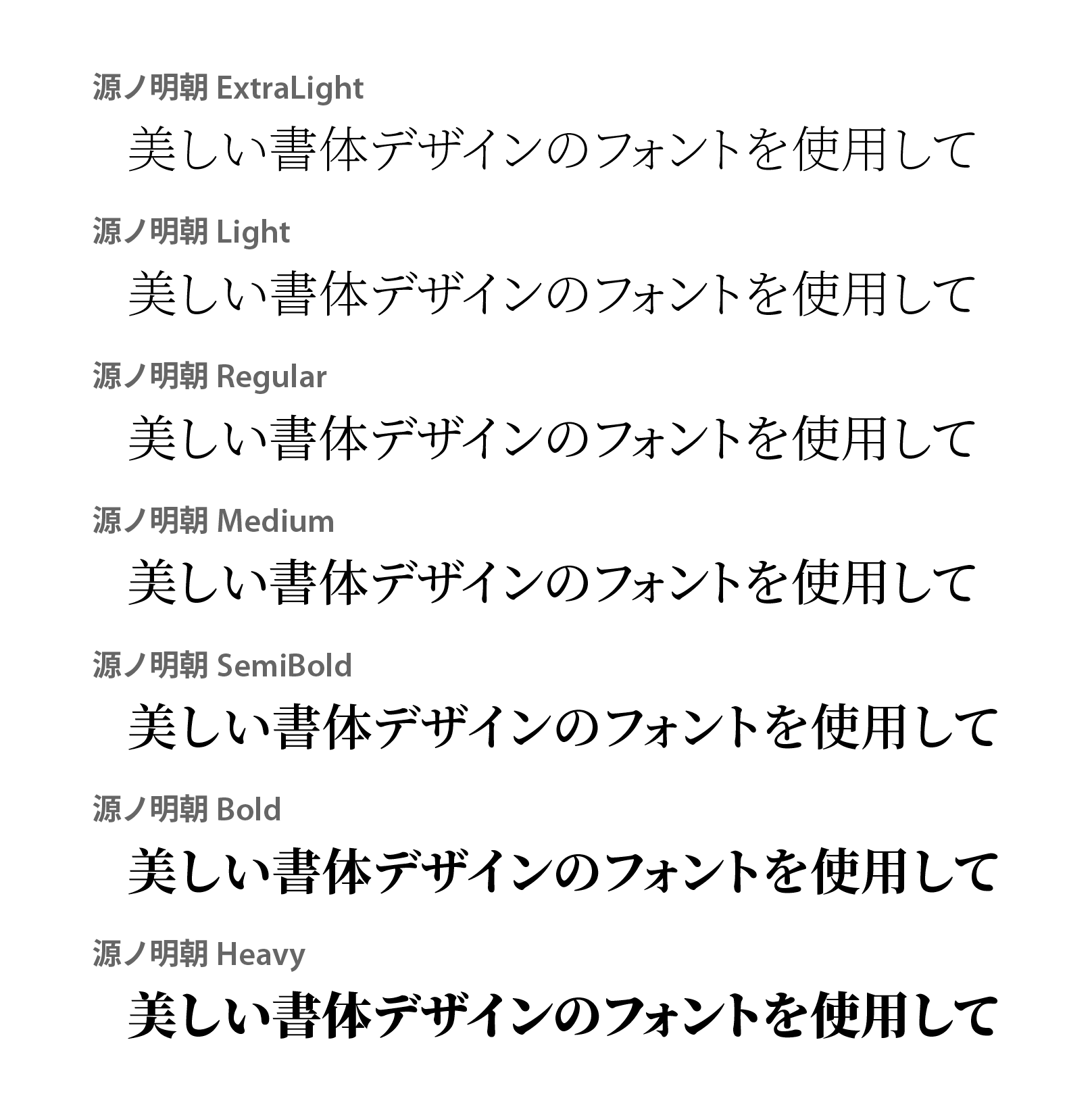
デザイン
「大きめの字面に対して、クラシックなフォルム」と解説されていました。
スモールデバイスでの表示を意識していることもあり、こうして比べてみると、横棒が圧倒的に太いですね。
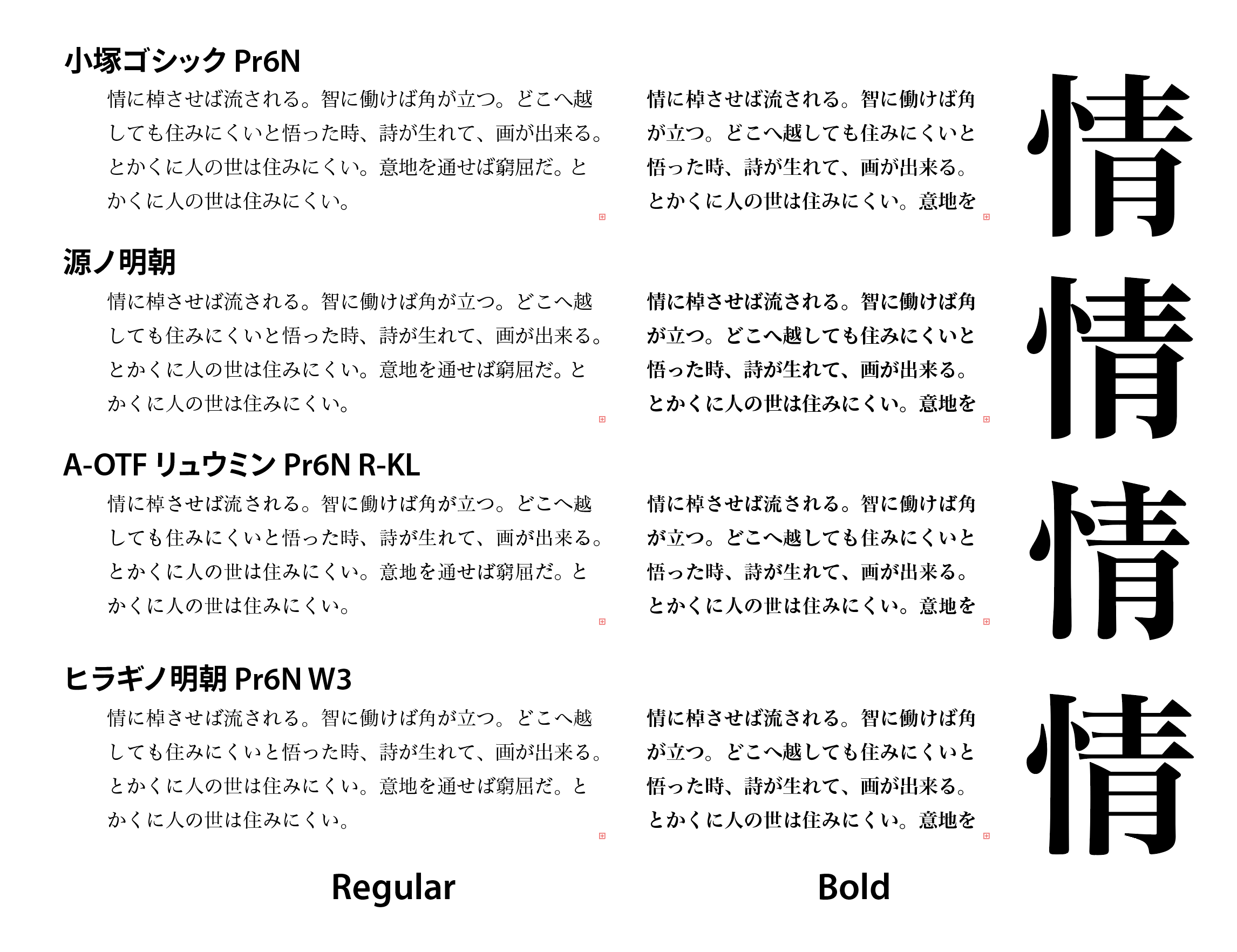
「源ノ明朝」というネーミング
- 「Source」をキーワードに名称を検討
- ソースだと「焼きそば明朝」と呼ばれてしまうかもと日本サイドで反対(こっちのソースはsauceだけど)
- Sourceを意味する「源」を使用することに
- フォント名としての固有性を高めるために「の」を追加。『風“の”谷のナウシカ』や『魔女“の”宅急便』のようにジブリメソッドを踏襲
ポイントはPan-CJK
CJKは、Chinese、Japanese、Koreanの略。東アジアで用いられている4つの言語(日本語、簡体中国語、繁体中国語および韓国語)で必要な文字をサポートすることが開発コンセプト。「Pan-」は、「全〜」といった意味合い。
ホテルや美術館など、多言語で掲示する必要があるケースでも、これまでは、フォントがないばかりに、不自然なフォントが使われていたり、
スーパーOTC
源ノ明朝および源ノ角ゴシックは、スーパーOTCに対応しています。
言語ごとにバラバラに使うだけでなく、それらを統合した1フォントとして使うことができるというもの。
Illustrator、InDesignでの利用
ウエイトの順番
Illustratorも30歳とのことで、そろそろ「アルファベット順」じゃなくて「ウエイト順」に表示してくれてもいいのにな、と思いません?
でも、冷静に見たら、「アルファベット順」でもなかった。何順??
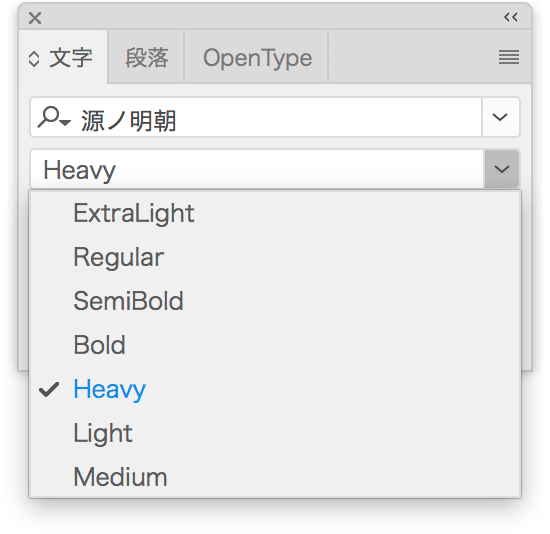
InDesignは、ウエイト順です…
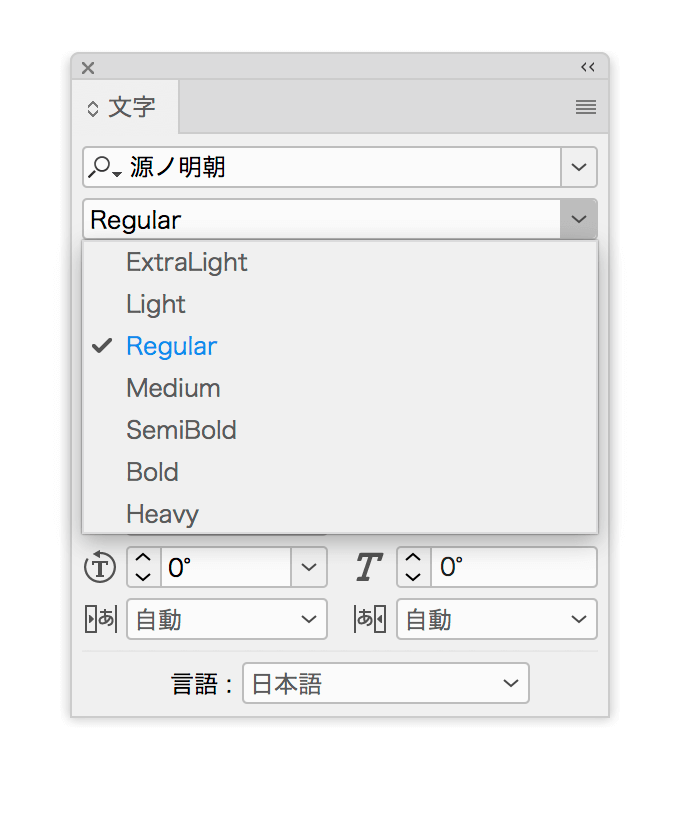
濁点
「源ノ明朝をこんな風に使って欲しい」というサンプルとして、次のスライドが提示されました。
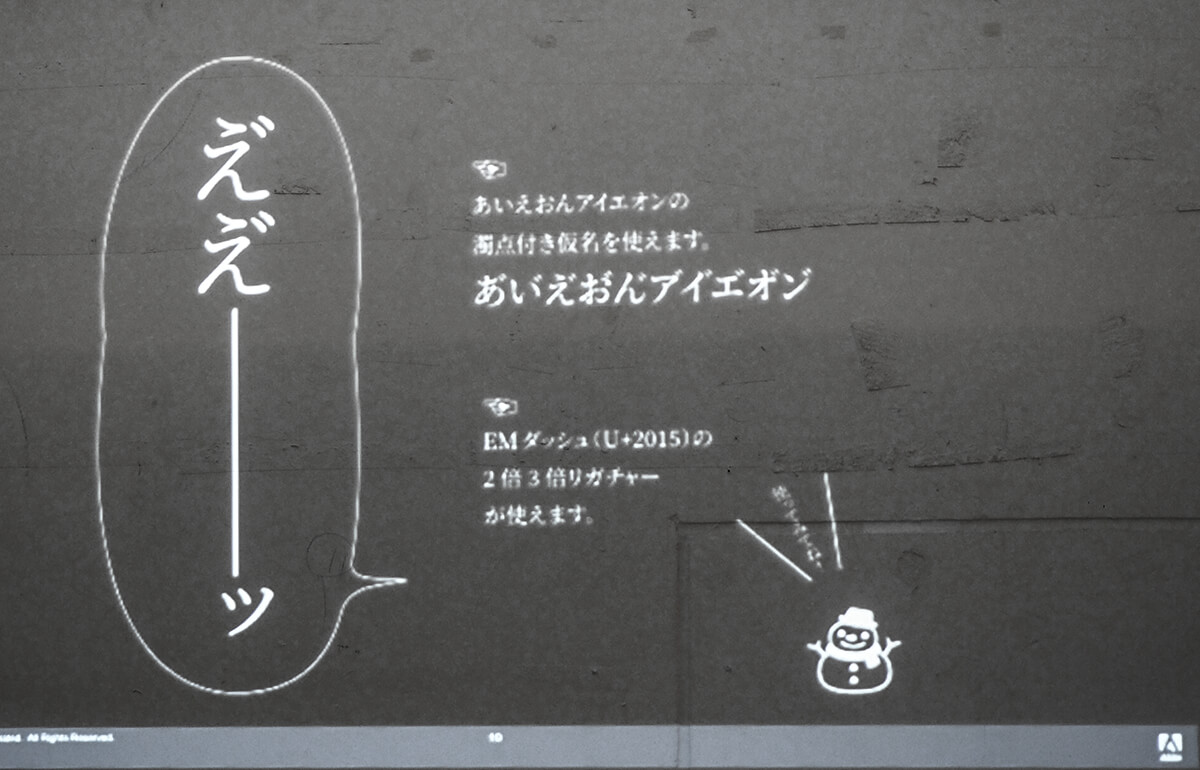
「え」に続けて、「゛」(だくてん)を入力すると、「濁点のついた“え”」になるハズですが、私の環境では、なぜかなりません。
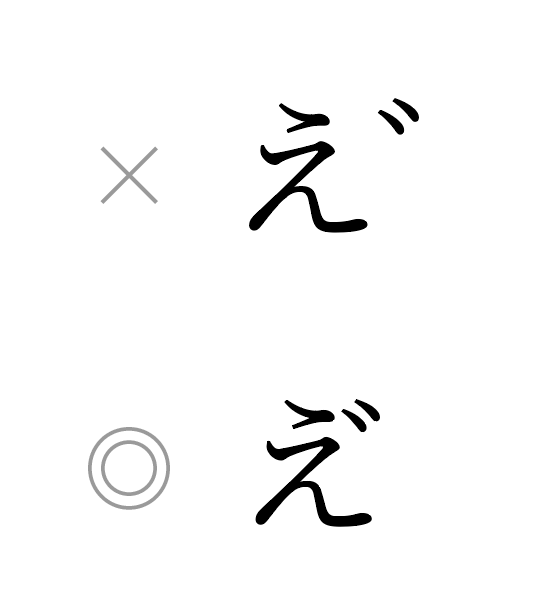
[字形]パネルの一番下の方にスクロールして、直接入力することはできます。
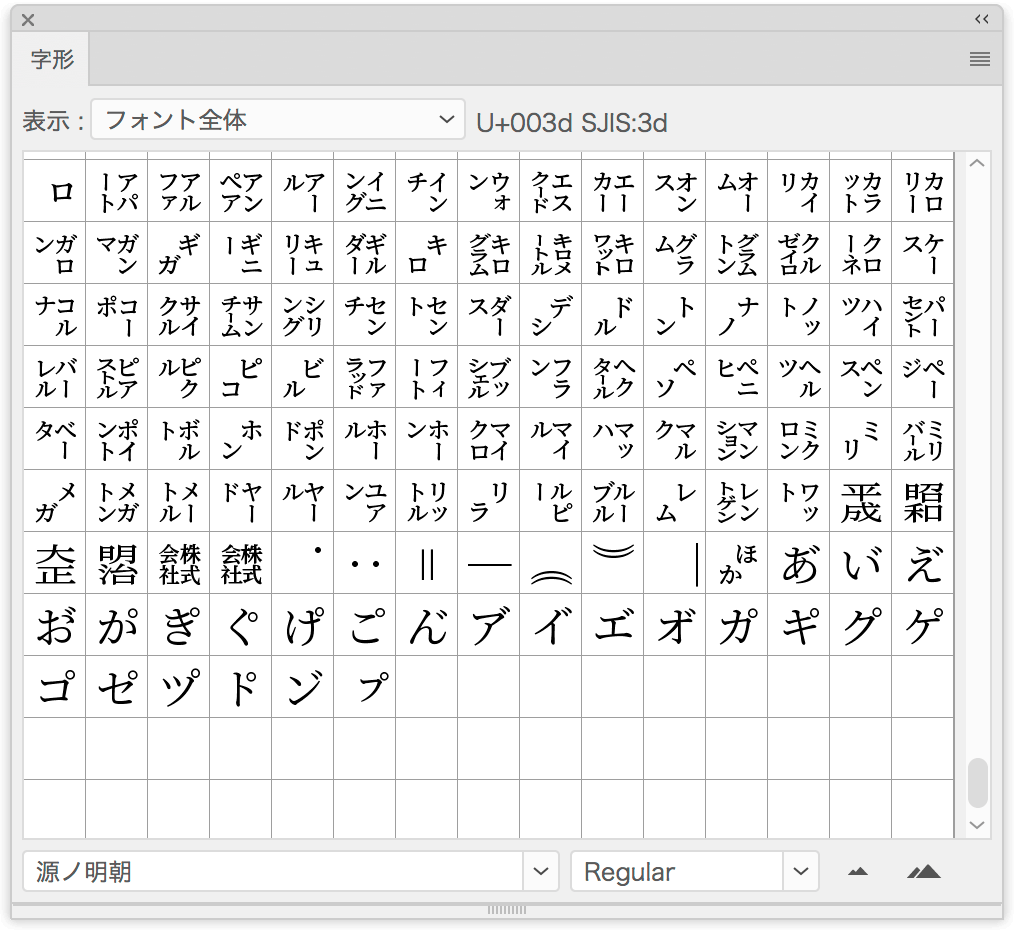
InDesignで調べてみると、確かに「309B」。
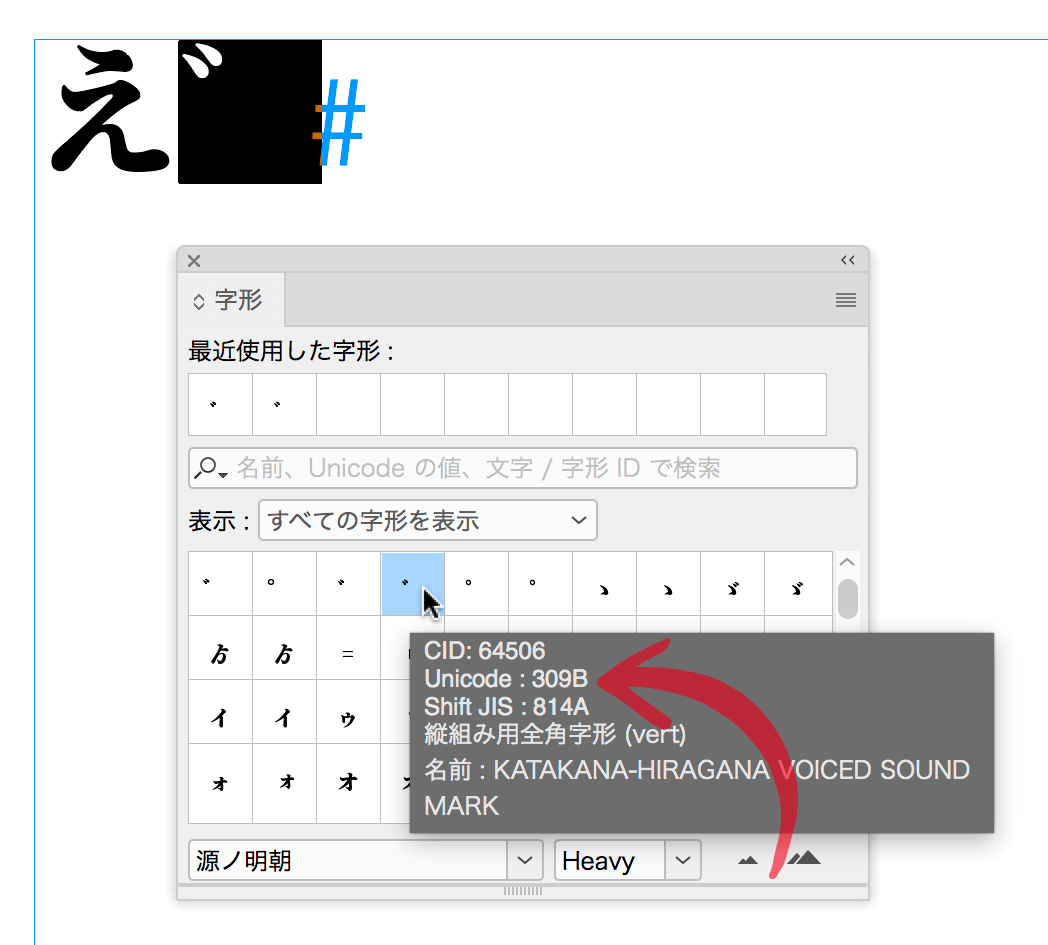
[字形]パネルの検索フィールドで「3099」を入れると、ちゃんと「濁点付きのえ」に変換されました。
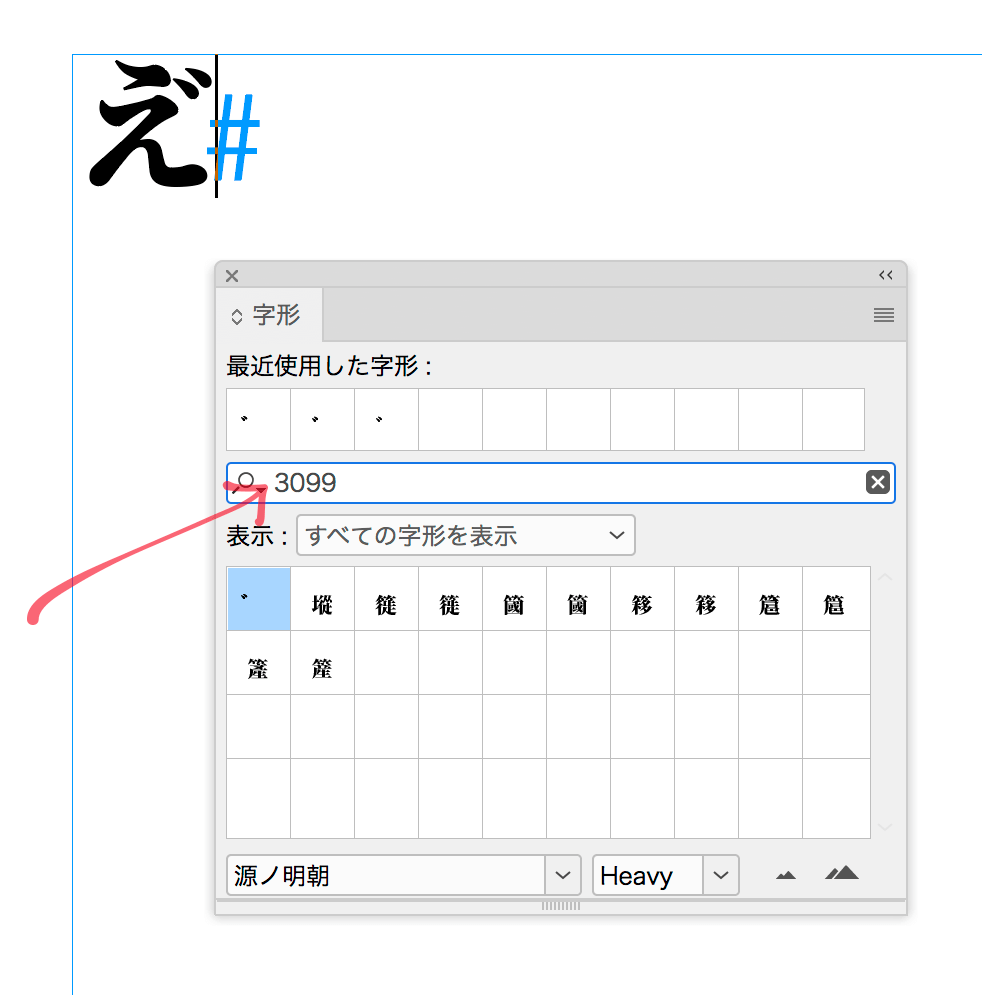
「3099」の濁点を単語登録したところ、IllustratorでもOKでした。
二倍ダーシ/三倍ダーシ
源ノ明朝では、ダーシを2つ、または、3つ続けて入力すると、合体したものに変換されます。しかし、Illustratorでは、縦書きのときに中心がズレてしまいます。
縦書きのときには、グリフを変更します。
縦組み用のかな
多くの明朝体は、縦組み用を基本に作ることが多い一方、源ノ明朝は横組み用を先にデザインし、追って、縦組み用をデザイン。
Illustrator、InDesignともに、縦組みにすると、自動的に変更されます。
Cap-Height数字の採用
英数字を単純に混植すると、日本語の中で小さく見えてしまいます。源ノ明朝では、「Cap-Height数字」を使って、この問題を回避するアプローチを取っています。
InDesignの[文字]パネルの[言語]で日本語を選択すると、ひとまわり大きいサイズになります。
一番画数の多い文字「ビヤン」
源ノ明朝は、「ビャンビャン麺」の「ビヤン」の文字をサポートしているそうです。
Illustrator、InDesignで次のように入力すると、
次の文字が表示されます。
とのことですが、「⿺」の次に半角スペースが入っているため、そのまま、コピー&ペーストしても実行できません。
源ノ角ゴシック、源ノ明朝の理想
佐藤好彦さんが、こんなツイートをされていました。賛成です!
フォントの日
日本記念日協会が認定とのことで、今年(2017年)からのようです。
世界的なコンピュータ・ソフトウェア企業の「アドビ システムズ 株式会社」が制定。デザインの重要な要素となっている「フォント」にあらためて注目してもらうことが目的。日付は4と10で「フォン(4)ト(10)」と読む語呂合わせから。
来年以降、いろいろとイベントが開催されるかもしれませんね。